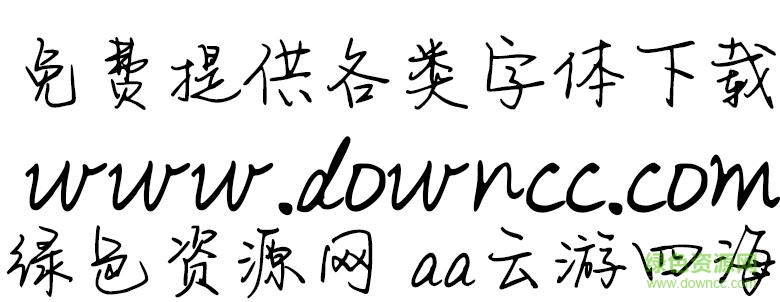
云游四海字體ttf
aa云游四海體字體是一款精美的擁有自主字體風(fēng)格,能夠讓你不斷感受到暢快的字體使用享受,這款讓人有種遺世獨(dú)立的感覺(jué),字形十分瀟灑流暢,看起來(lái)很舒服,大家可以在綠色資源網(wǎng)下載使用哦!
aa云游四海ttf小編點(diǎn)評(píng)
aa云游四海字體在使用的時(shí)候真的驚艷到了我,很好看,很獨(dú)特,是一款十分瀟灑的字體,每一個(gè)字體都很隨意,就像一個(gè)鋼筆字大師所寫的字體!
aa云游四海ttf
字形瀟灑,自由隨性,年少時(shí)的夢(mèng)幻想在遠(yuǎn)方,想落星湖的花海萬(wàn)里,遙遙難及,像陽(yáng)光落在赤道與北極,不爭(zhēng)朝夕